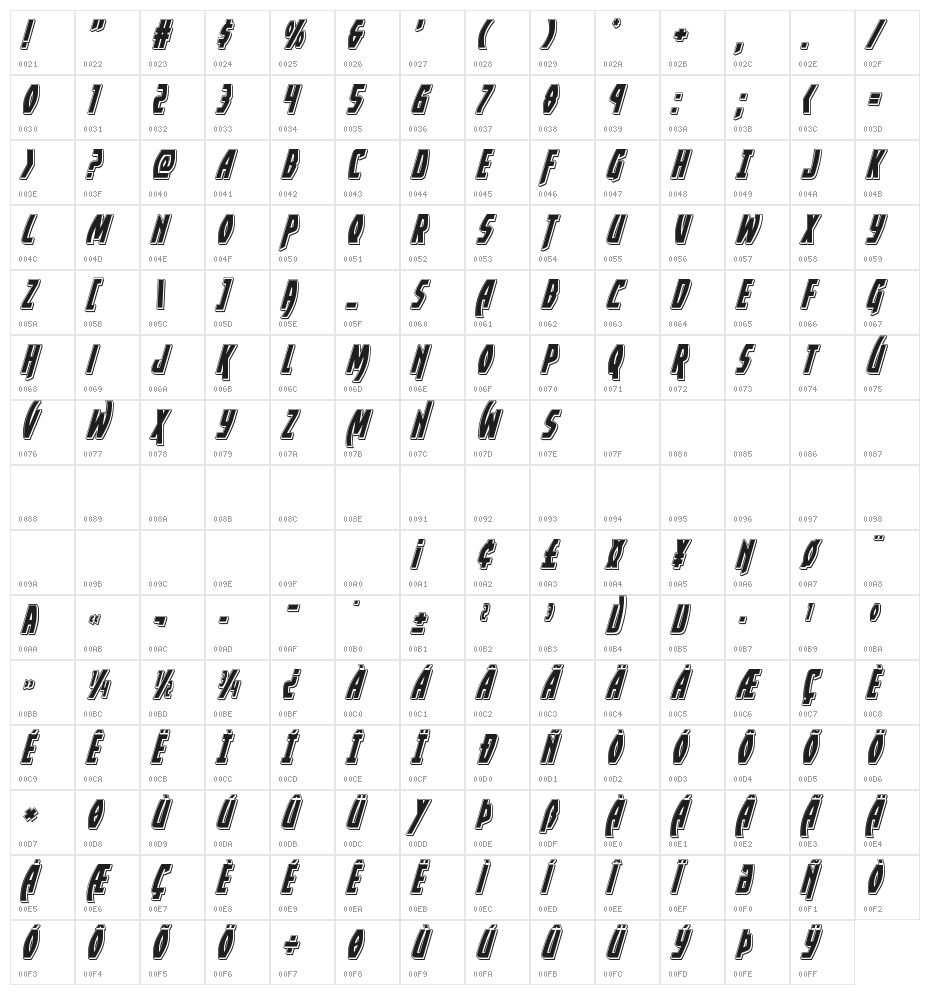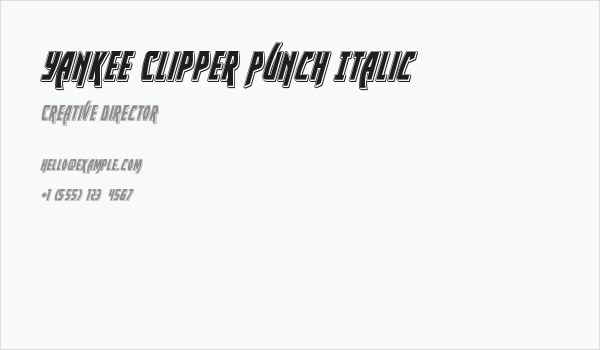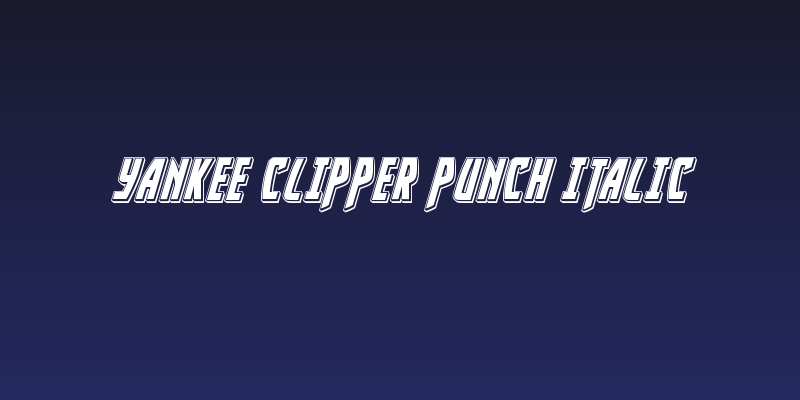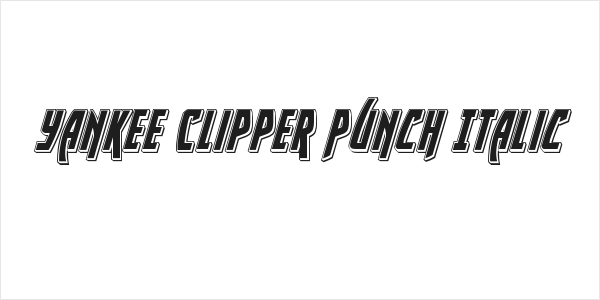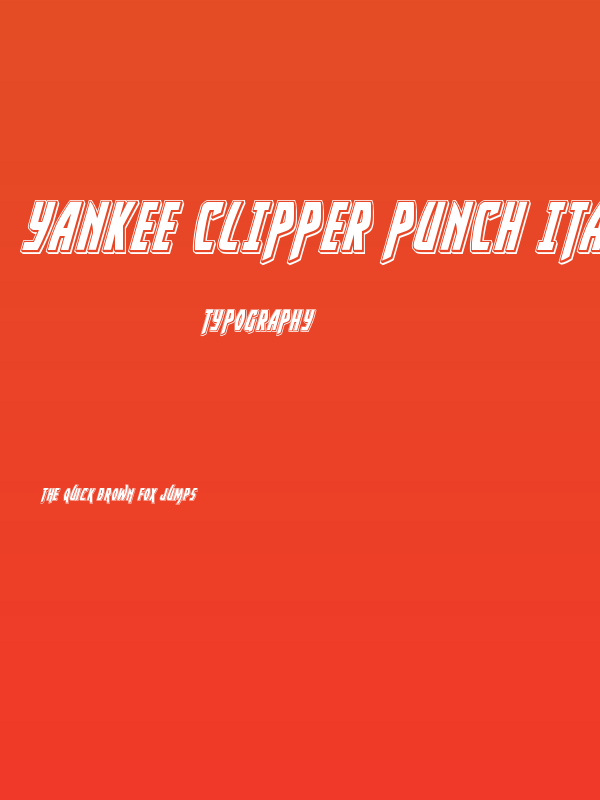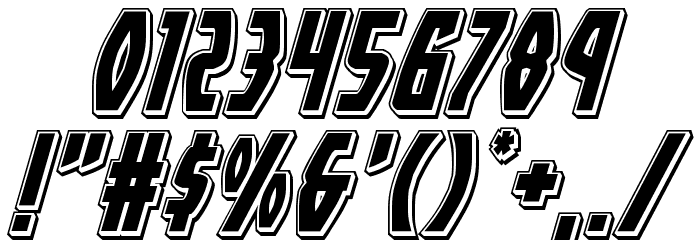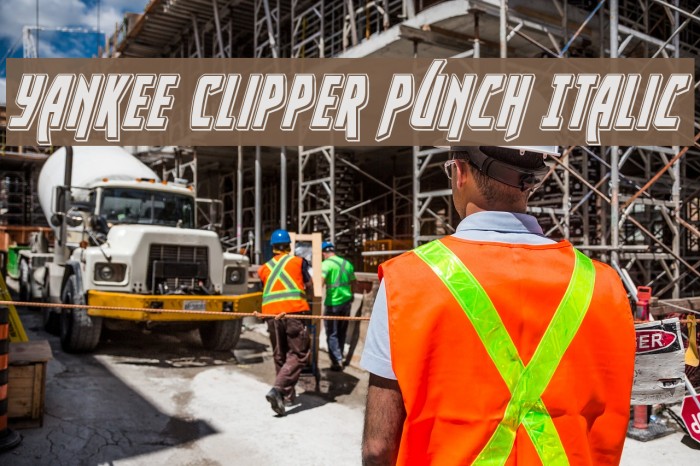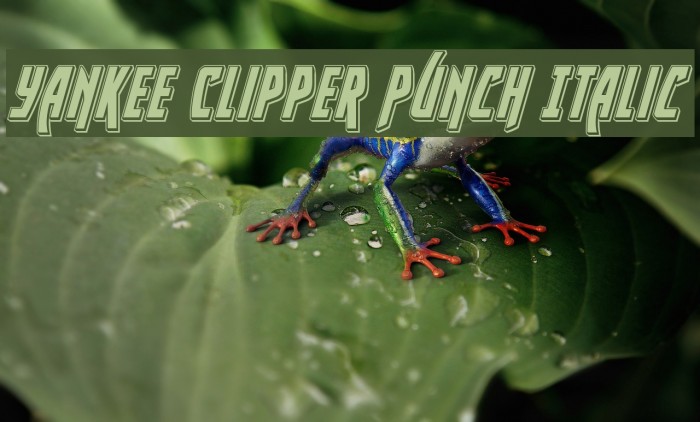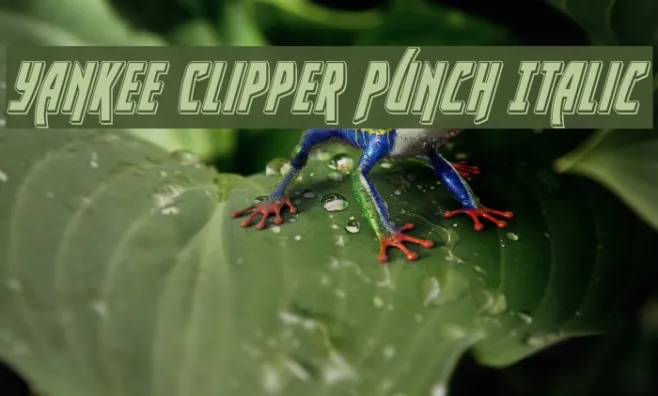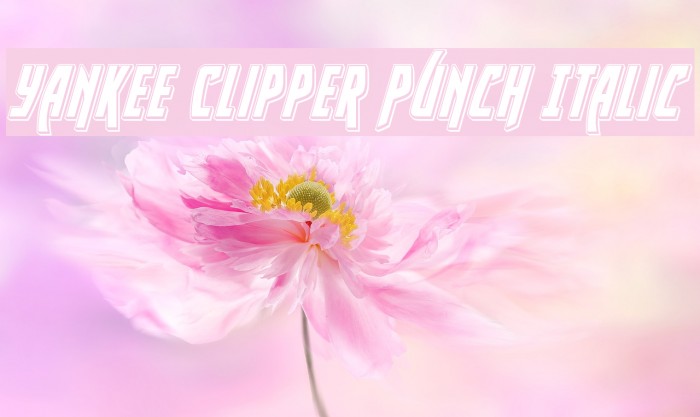
Yankee Clipper Punch Italic Font
| Proyectos propuestos | Perfect for sports team logos, action movie posters, or any design needing a bold, energetic typeface. |